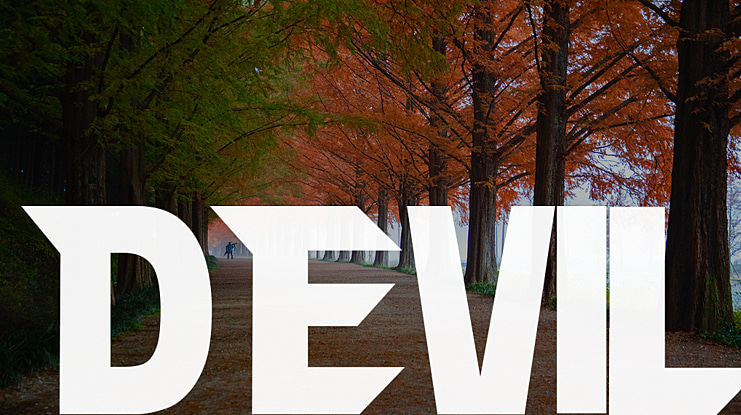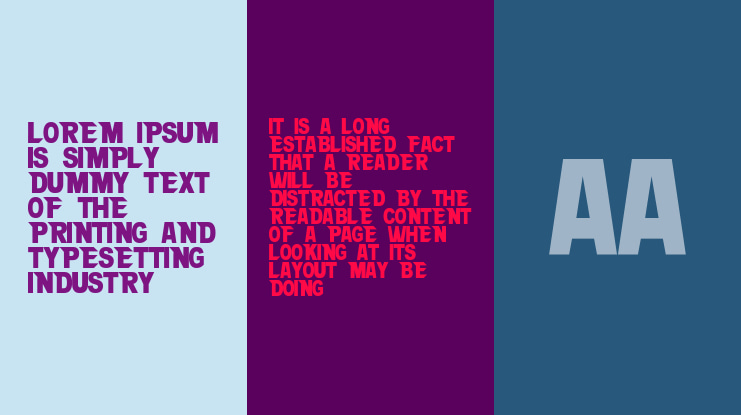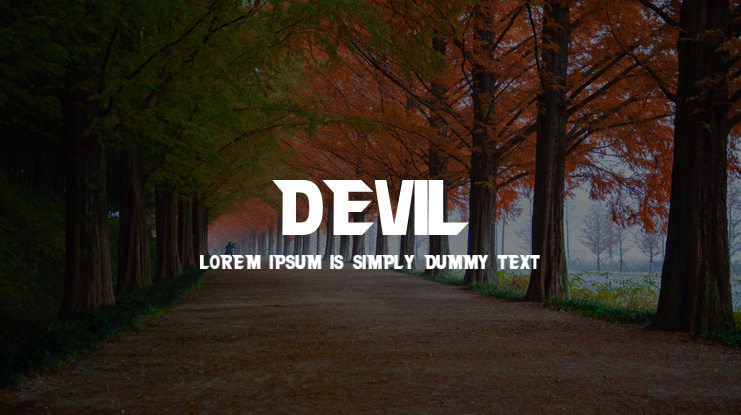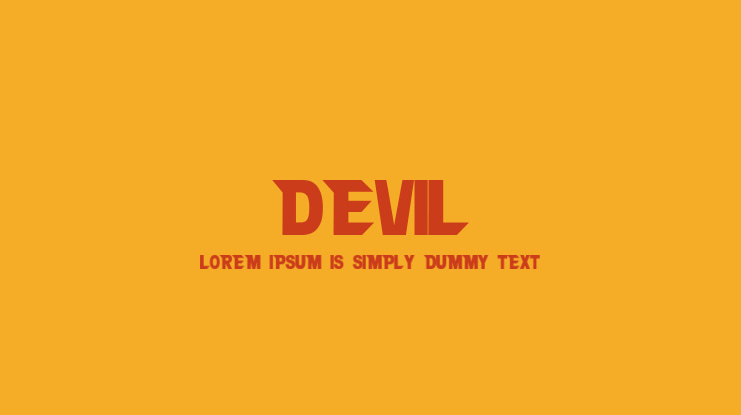
DEVIL Font
Direttamente dalla serie televisiva prodotta da Drew Goddard e interpretata da Charlie Cox, il font inedito per tutti gli estimatori del film.
Directly from the television series produced by Drew Goddard and starring Charlie Cox, the unpublished font for all admirers of the film.